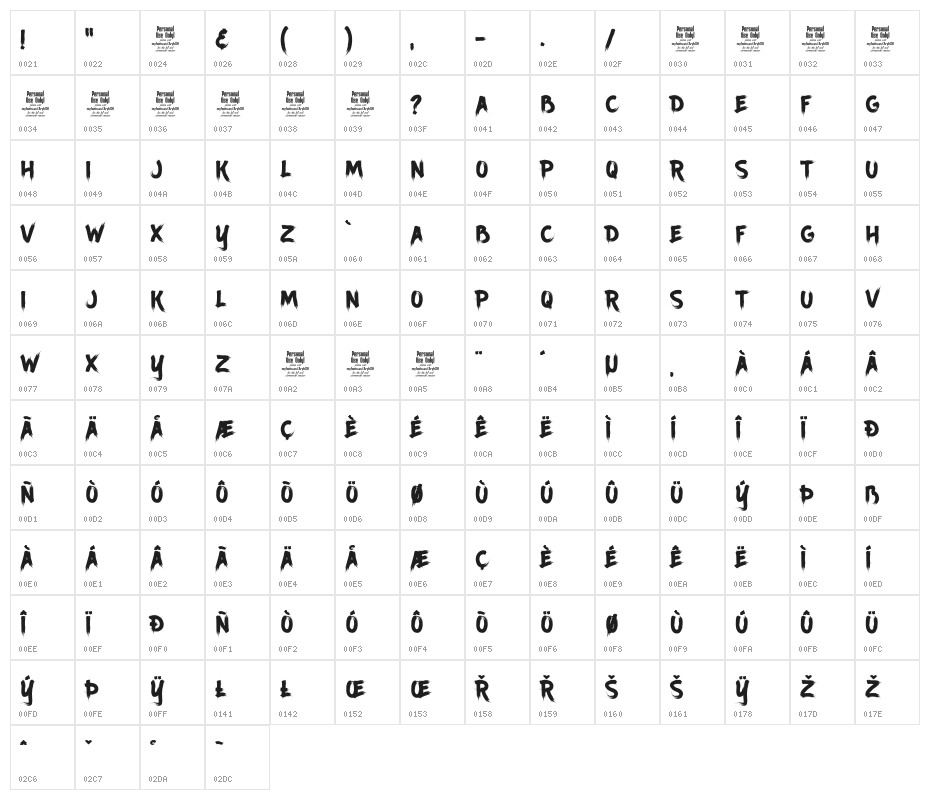
Ancherr Personal Use Font
| Progetti proposti | Ideal for projects that require a strong visual impact, such as posters, album covers, branding for edgy or artistic products, and event promotions. |